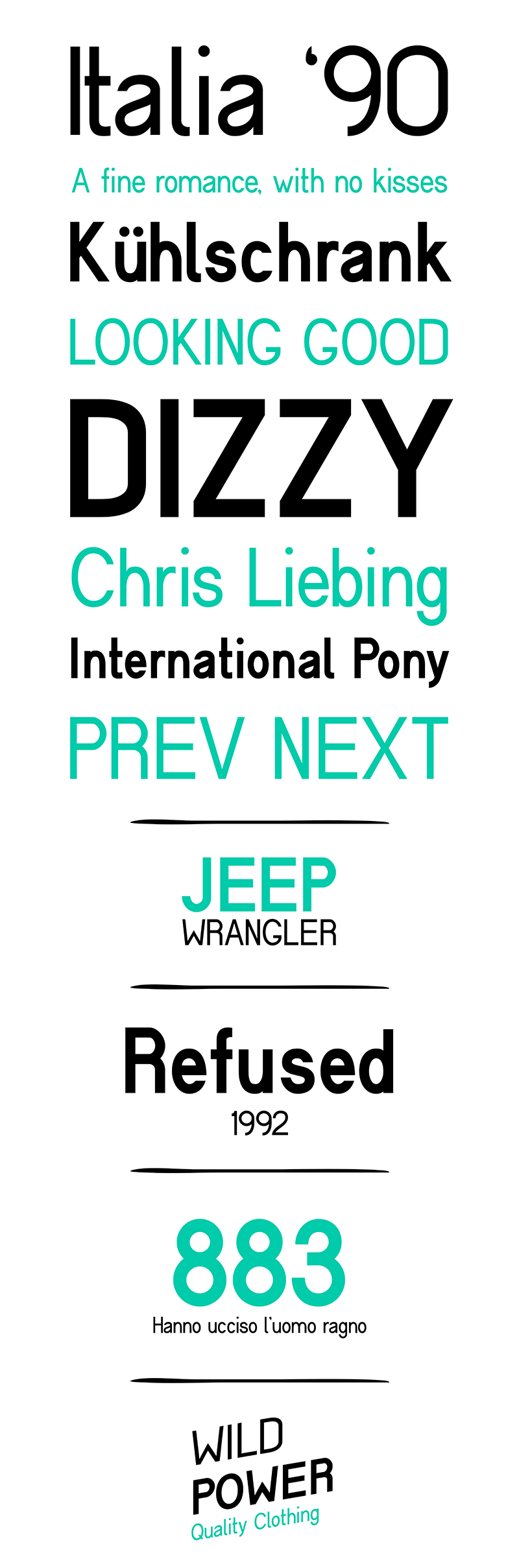
Cerbetica é uma tipografia Geometrica Sans Serif projetada para se assemelhar ao famoso Helvetica, que é considerado entre os mais populares de todas as fontes existentes. Inspirada na simplicidade geométrica de Helvetica, a Cerbetica mantém um alto nível de legibilidade tanto para uso em displays quanto para textos, tornando-a perfeita não apenas para ambientes digitais mas também para o design gráfico tradicional. Com seu design limpo e minimalista, esta fonte é uma opção versátil que consegue transmitir mensagens eficazmente de forma independente. Perfeita tanto para uso em sites quanto na tipografia, a Cerbetica se destaca pela sua simplicidade, tornando-a perfeitamente legível mesmo em tamanhos muito pequenos. A qualidade desta fonte não só melhora o seu impacto visual no design gráfico, mas também garante que a comunicação seja compreendida de forma clara e eficiente independentemente do tamanho da exibição.